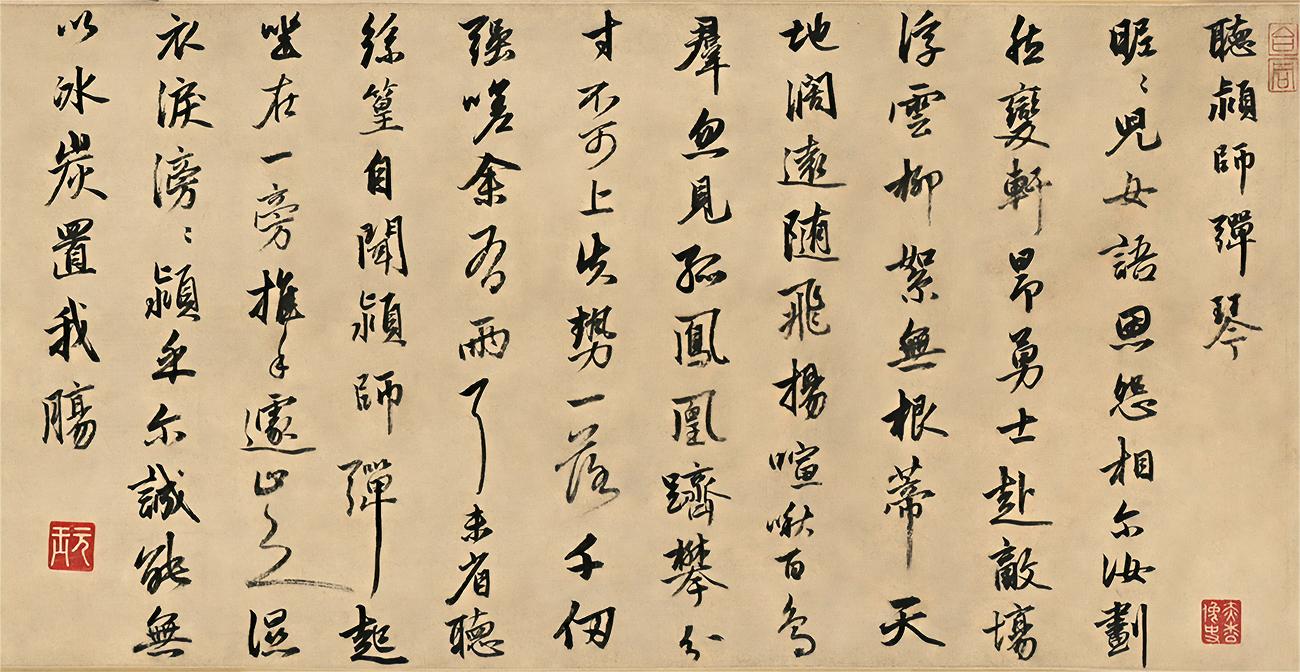
汉标明代金琮听颖师弹琴 By 真迹小字库 商用字体
字体简介: 下载须知:本字库非标准GB2312字库。本字库只包含了金琮《听颖师弹琴》真迹上的“123个字”。金琮,明代书画家,字元玉,自号赤松山农,金陵 (今南京) 人。由于金琮的书法很似赵书,故很多金琮的字,即使不是有意作伪,也被后人挖去原款,添上“赵孟頫”三字,以欺世人。明代金琮书法韩愈诗《听颖师弹琴》,北京故宫博物院藏。